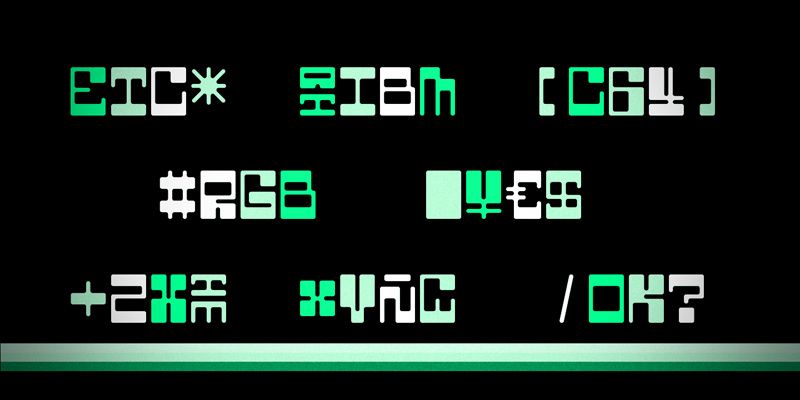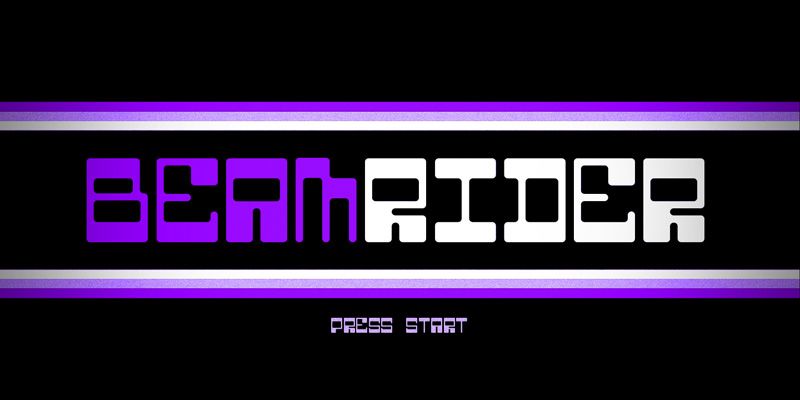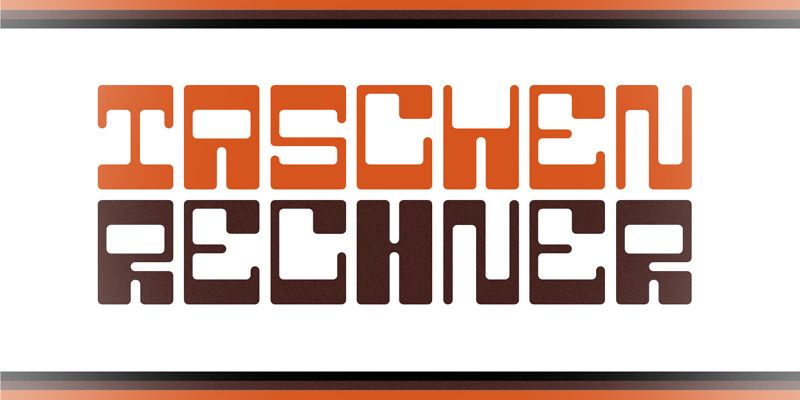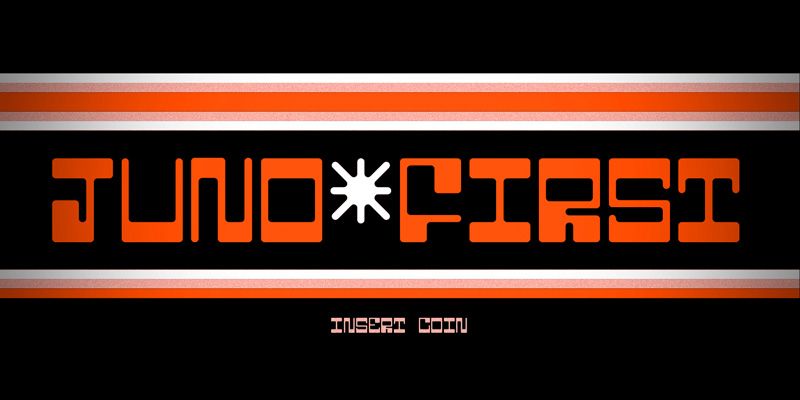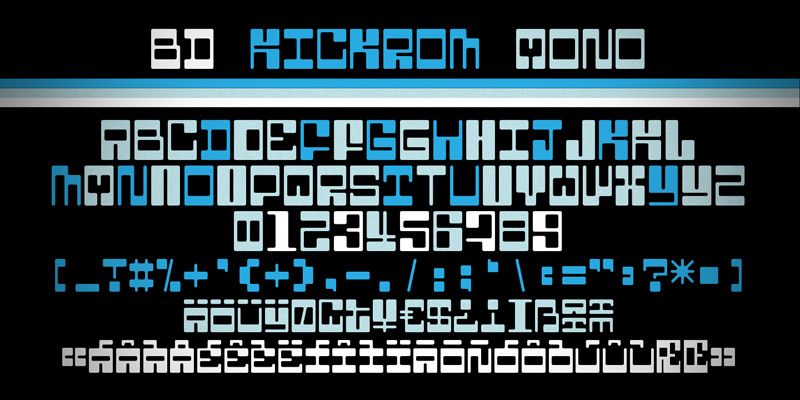
BD Kickrom Mono ist eine retrofuturistische, monospaced Großbuchstabenschrift mit Varianten bei den Kleinbuchstaben. Entworfen von Lopetz im Jahr 2016.